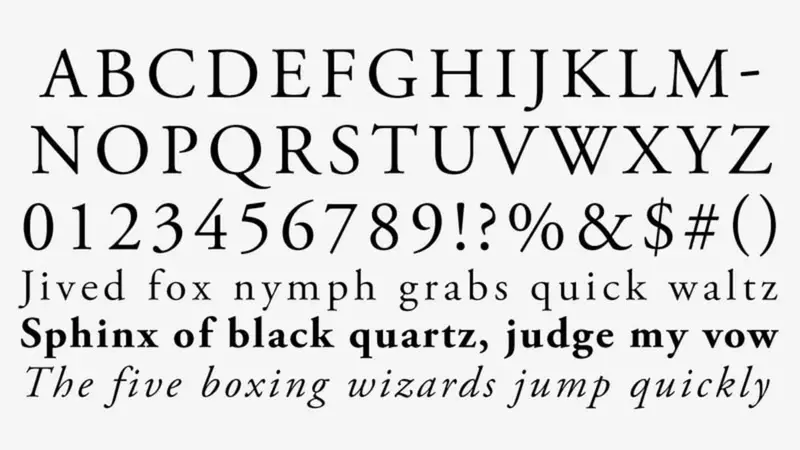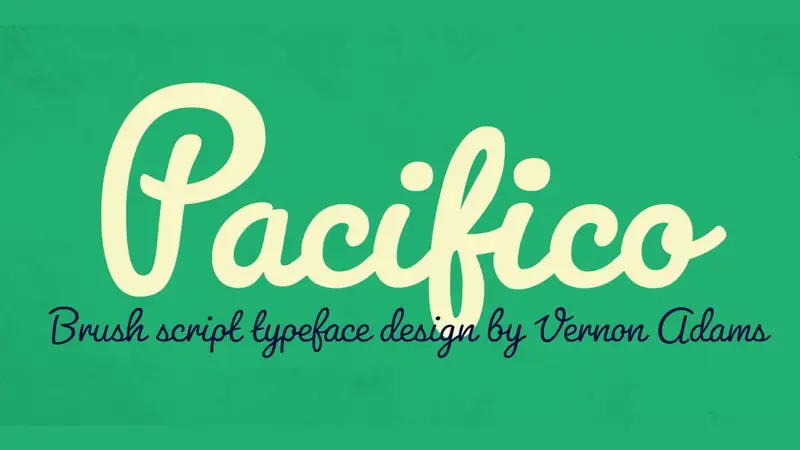
10+ Jenis Font Keren Untuk Logo, Asli Keren Nih DOWNLOAD DISINI!
Memilih jenis font yang tepat untuk logo sering dianggap sepele. Padahal, rupa huruf memiliki peranan penting dalam merepresentasikan identitas merek, berikut tujuan yang ingin dicapai. Selain itu, masing-masing font memiliki estetika dan kecocokan berbeda dengan desain logo untuk menarik perhatian target pasar. Jadi, apa saja jenis font yang sebaiknya dipertimbangkan?
Font untuk logo yang keren pertama adalah Garamond. Rupa huruf ini adalah sekelompok huruf berkait (serif) dengan gaya klasik yang dirancang oleh orang Prancis bernama Claude Garamond pada abad ke-16. Tidak heran jika nama belakangnya kemudian diambil sebagai penamaan untuk font yang ditemukannya. Garamond sangat sering digunakan karena mudah dibaca.
Font logo keren ini memiliki banyak variasi seiring perkembangan zaman, yaitu: Adobe Garamond, Stempel Garamond, EB Garamond, Sabon Next dan ITC Garamond. Selain mudah terbaca, Garamond juga memberikan sentuhan elegan ketika diaplikasikan. Sebab itu, tidak hanya untuk logo, Garamond juga menjadi pilihan untuk diimplementasikan pada buku cetak, website, dan aplikasi.
Jenis font keren untuk logo lainnya adalah Helvetica. Font ini dikembangkan pada tahun 1957 oleh Max Miedinger bersama Eduard Hoffmann di Swiss. Rupa huruf ini juga menjadi yang paling banyak digunakan untuk kebutuhan desain grafis oleh para profesional. Selain mudah dibaca dan estetik, Helvetica juga sederhana dan memiliki kompatibilitas tinggi.
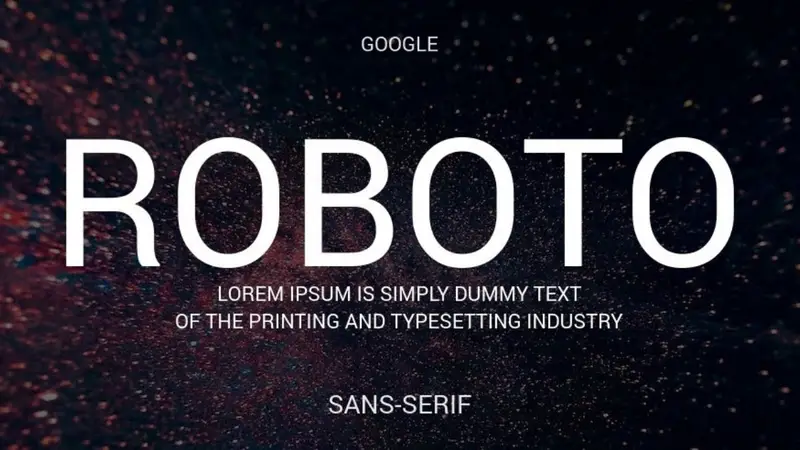
Font keren untuk logo nama yang bisa kamu pertimbangkan adalah Roboto. Rupa huruf ini diciptakan oleh Christian Robertson, seorang in-house desainer Google pada tahun 2011. Font ini semula dibuat untuk kebutuhan sistem bawaan Android 4.0 alias Ice Cream Sandwich. Bentuk hurufnya sederhana, bersih, dan mudah terbaca merupakan konsep font Roboto.
Meskipun sempat tidak lagi digunakan pada Android 5.0 atau Lollipop, nyatanya, Roboto kembali digunakan sebagai font sistem pada Android 6.0 dan selanjutnya setelah sang pemilik hak cipta melakukan beberapa perbaikan. Roboto kini menjadi jenis font keren bawaan untuk semua perangkat, aplikasi, dan situs berbasis Google. Tentu juga menarik untuk logo.
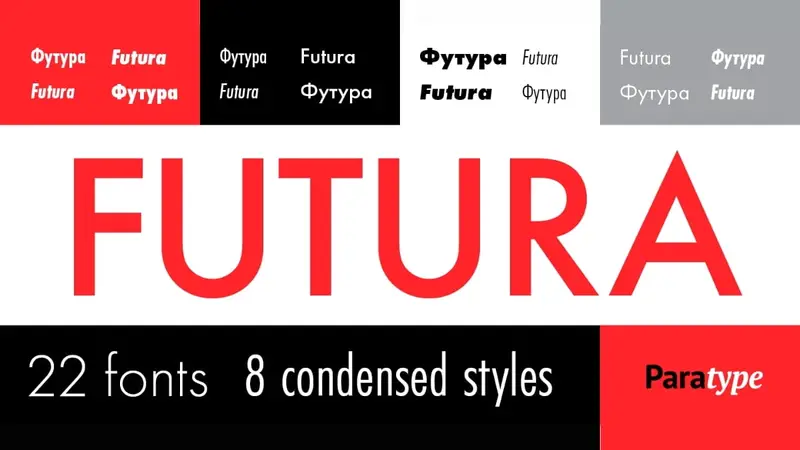
Jenis font yang bagus untuk logo berikutnya adalah Futura. Rupa teks ini dirancang oleh Paul Renner dan dirilis pada tahun 1927. Prinsip utamanya adalah bentuk geometris, sehingga sudut lingkaran, kotak, dan segitiga pada masing-masing hurufnya nyaris sempurna. Mengaplikasikannya pada logo produk atau perusahaan dapat menyimbolkan kredibilitas dan integritas yang dimiliki.
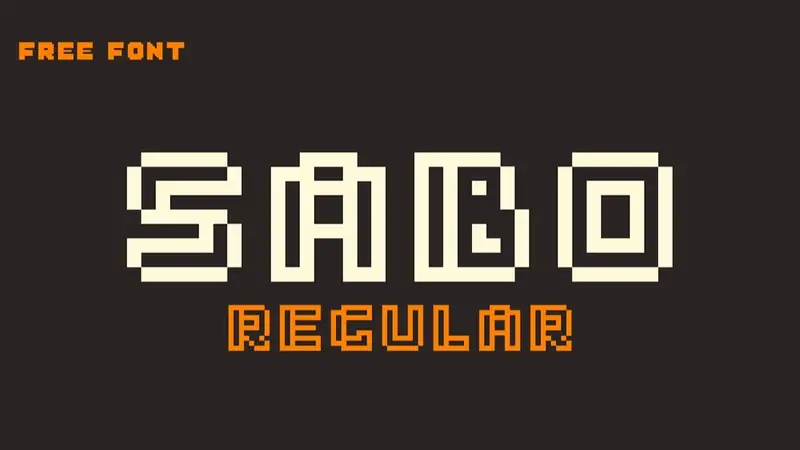
Membedakan font yang satu ini semudah menemukan perbedaan gambar vektor dan bitmap. Sebab, ciri khasnya tampak jelas, yaitu menggunakan bentuk menyerupai piksel karena memang, Philippe Moesch; seorang desainer grafis sekaligus penciptanya, terinspirasi teks game 8-bit. Font ini cocok untuk digunakan pada logo, khususnya berkaitan teknologi, fotografi, desain grafis dan sejenisnya.
Namun, sebaiknya implementasinya untuk logo atau objek cetak lain yang ditujukan pada generasi muda atau usia produktif. Sebab, bila target audience-nya lanjut usia, akan kesulitan untuk membaca dan mengenali jenis rupa teks yang satu ini. Menarik dan estetik, tetapi tidak dapat dipungkiri bahwa tingkat kesesuaiannya sangat terbatas – khususnya terkait pemirsa.
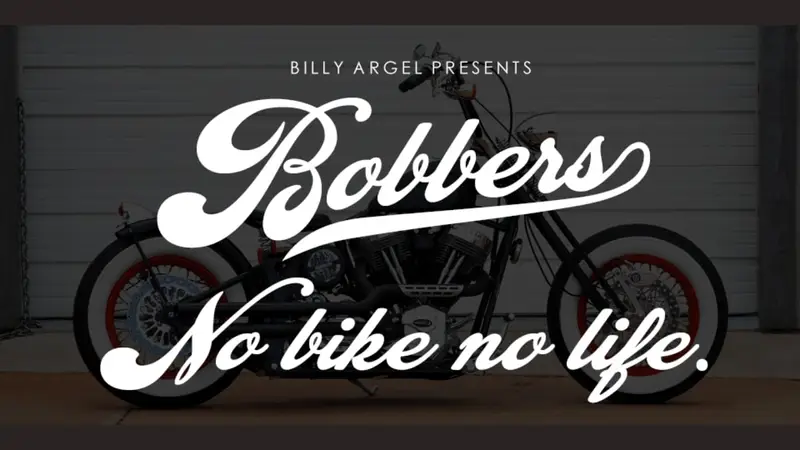
Font desain logo lainnya adalah Bobbers. Lucas Almeida dan Dmitry Goloub merupakan pencipta rupa teks bergaya vintage yang satu ini. Ciri khasnya menyerupai hasil kaligrafi lain yang estetik, elegan, dan tentu bernuansa nostalgia. Jenis yang cocok untuk Anda implementasikan pada logo yang berkaitan dengan membangkitkan kenangan, contohnya untuk re-branding produk.
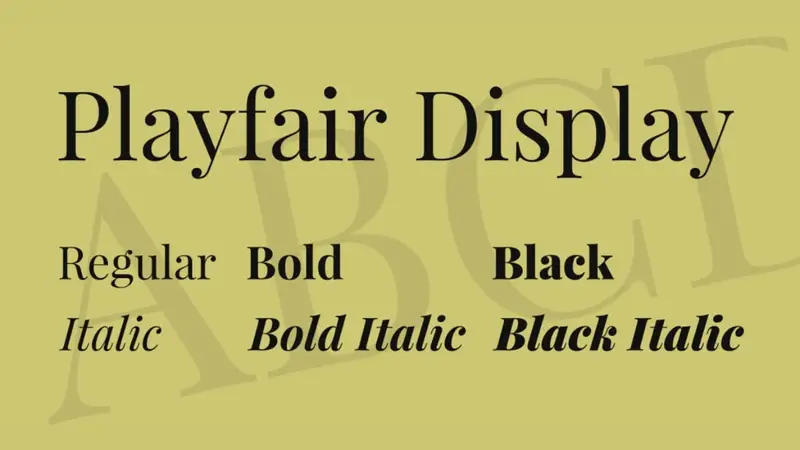
Merupakan jenis font transisi yang didesain oleh Claus Eggers Sørensen di tahun 2011. Desainnya terinspirasi oleh Baskerville dan Scotch Roman yang telah hadir sejak abad ke-18. Memadukan gaya lama rupa huruf Serif dengan gaya yang baru – lebih modern. Cocok diimplementasikan pada jenis format gambar JPG, SVG, atau PNG untuk logo.
Ciri khas font ini simetris, sehingga tidak hanya untuk logo, biasanya sering dipakai untuk tajuk utama berita atau penulisan undangan. Jenis font ini memberikan sentuhan klasik yang kuat dan tentu saja elegan serta menarik. Playfair Display hadir dalam mode bold dan italic , selain normal, untuk kamu pilih penggunaan sesuai kebutuhan.
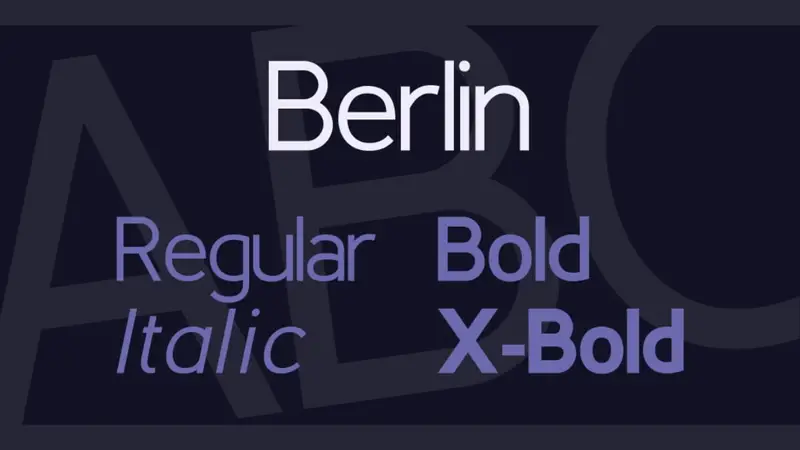
Semudah mengenali perbedaan rgb dan cmyk, kamu juga akan mudah mengenali jenis font yang cukup populer ini. Rupa teksnya termasuk dalam kategori huruf geometris sehingga masing-masing penulisannya simetris, seperti Futura. David Berlow, di tahun 1997, menciptakan font dengan tampilan minimalis alias sederhana ini. Namun, justru itulah yang daya tarik utamanya.
Font ini dapat dikombinasikan dengan mudah pada desain logo atau lainnya seperti cetak buku. Psikologi warna dalam desain yang diterapkan saat penggunaan font ini juga akan membuat tampilan akhir lebih cantik. Khususnya yang menekankan konsep minimalis tapi berkelas. Rupa teks Berlin memiliki 4 jenis berbeda: Berlin, Berlina, Slaberlin dan Uberlin.